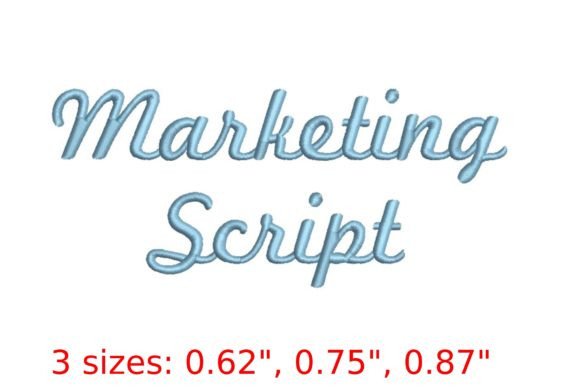
Marketing Script Embroidery Font
Encontrar os elementos de design certos pode ser um desafio, mas Marketing Script Embroidery Font oferece uma coleção excepcional que eleva o seu trabalho instantaneamente.
Trabalhado com precisão, Marketing Script Embroidery Font fornece vetores limpos, tipografia suave e uma licença comercial para sua tranquilidade.
Quer você esteja criando produtos POD (Print on Demand), convites de casamento ou gráficos para mídias sociais, Marketing Script Embroidery Font é a escolha ideal.